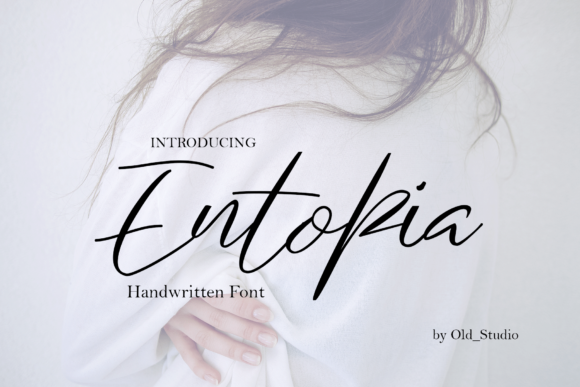
Entopia Script Font
Entopia Script Font é uma elegante fonte tipográfica de escrita cursiva que traz os melhores elementos do estilo do desenho a lápis. Esse tipo de letra moderno e moderna se destaca por sua linha suave, traços variados no nível básico e um toque clássico e sofisticado. A Entopia é uma fonte de escrita cursiva que não apenas captura o espírito contemporâneo da grafia criativa, mas também oferece suporte a múltiplas línguas internacionais. Obrigado ao designer 0001themes por este trabalho meticuloso, Entopia Script Font inclui um completo conjunto de letras maiúsculas e minúsculas, símbolos multilíngues, números e pontuação. Além disso, ela também oferece ligações apropriadas para aqueles desejosos de mais detalhes em sua produção gráfica. Esta fonte é ideal tanto para designers como para criadores de conteúdo que buscam uma maneira de introduzir um toque de sofisticação e originalidade em seu design. A Entopia Script Font, com certeza, fará a diferença em qualquer projeto onde deseja incorporar um toque de elegância à sua arte visual.